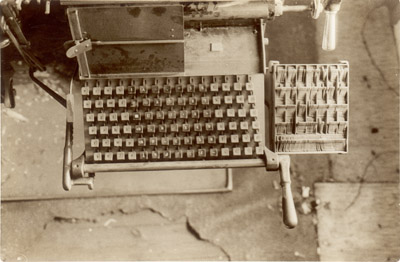
linotype tastaturlayout
hat jemand von euch eine ahnung, ob die linotype sowohl mit englischem als auch mit deutschem tastaturlayout hergestellt wurde?
die tastaturbelegung erfolgte doch immer nach der buchstabenhäufigkeit einer sprache. daher auch das etaoin shrdlu im englischen, was allerdings im deutschen kein äquivalent hat. ich versuche grad zu ergründen, wieso.
weil es die linotype gar nicht mit deutschem tastaturlayout gab?
Ich glaube schon; soweit ich weiss wurde die Linotype auch in den USA verwendet.
weil es die linotype gar nicht mit deutschem tastaturlayout gab?
Doch, klar gab's die auch mit deutscher »Klaviatur«, wie die Tastatur an der Linotype hieß, und sicher auch etwa in Französisch, Spanisch etc. Hier findest Du ein PDF mit einigen Bildern von der Linotype. Wenn Du auf Seite 3 mal mit 800% reinzoomst, kannst Du auch die deutsche Belegung sehen.
hat jemand vielleicht eine ahnung, wieso es im englischen zur verwendung von etaoin shrdlu als platzhalter kam, im deutschen die entsprechende buchstabenfolge allerdings nicht in der funktion als zeilenfüller verwendet wurde?
Nur eine Vermutung …
Die Linotype-Tastatur – äh, Klaviatur – ist nicht wie eine Schreibmaschine belegt, sondern absteigend nach der Häufigkeit der Buchstaben:
etaoin
shrdlu
[cmfgyp
wbvkxj qz]
In dem von Lars geschickten Bild sieht man, dass die deutsche Klaviatur womöglich auch nach der – natürlich verschiedenen – Häufigkeit belegt wurde; x, y, z stehen jedenfalls ganz unten.
In dem von Lars geschickten Bild sieht man, dass die deutsche Klaviatur womöglich auch nach der – natürlich verschiedenen – Häufigkeit belegt wurde; x, y, z stehen jedenfalls ganz unten.
richtig, die entsprechende buchstabenfolge müsste laut wikipedia lauten ENISRA TDHULC. nur steht da auch, dass es im deutschen keine dem etaoin vergleichbare tradition gibt. ich versuche halt grad zu ergründen, wieso nich...
wie haben denn unsere linotyper sinnlostexte verfasst?